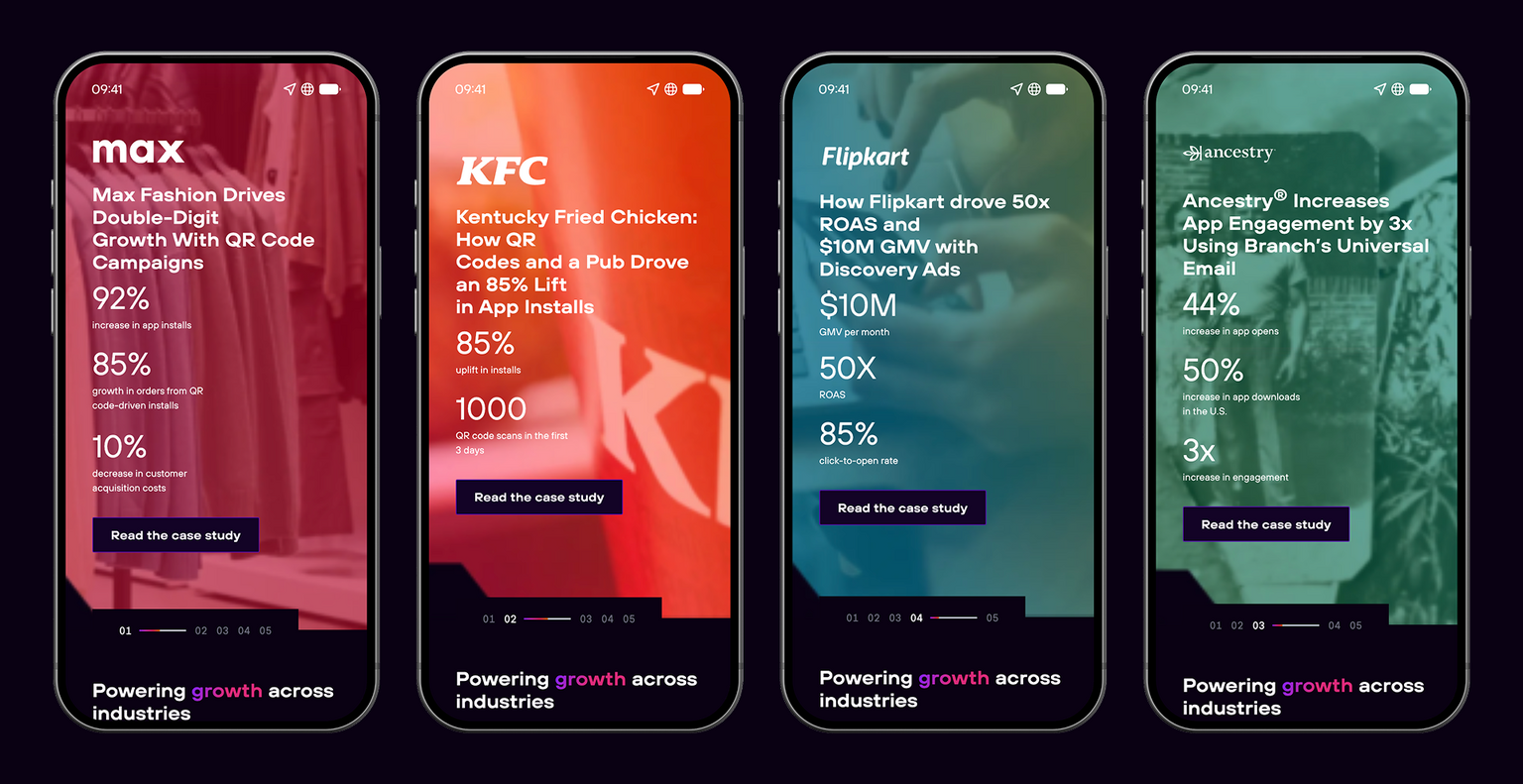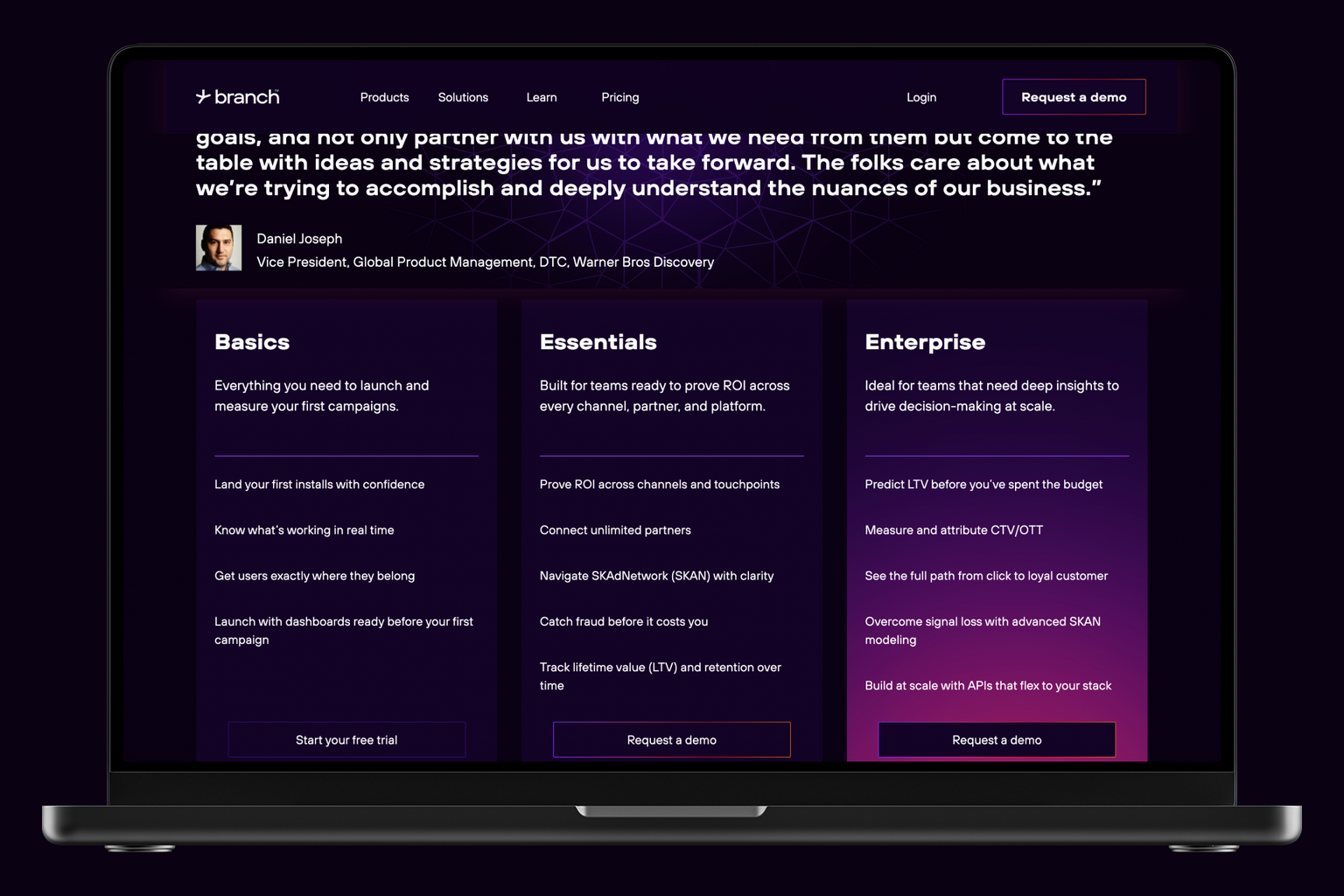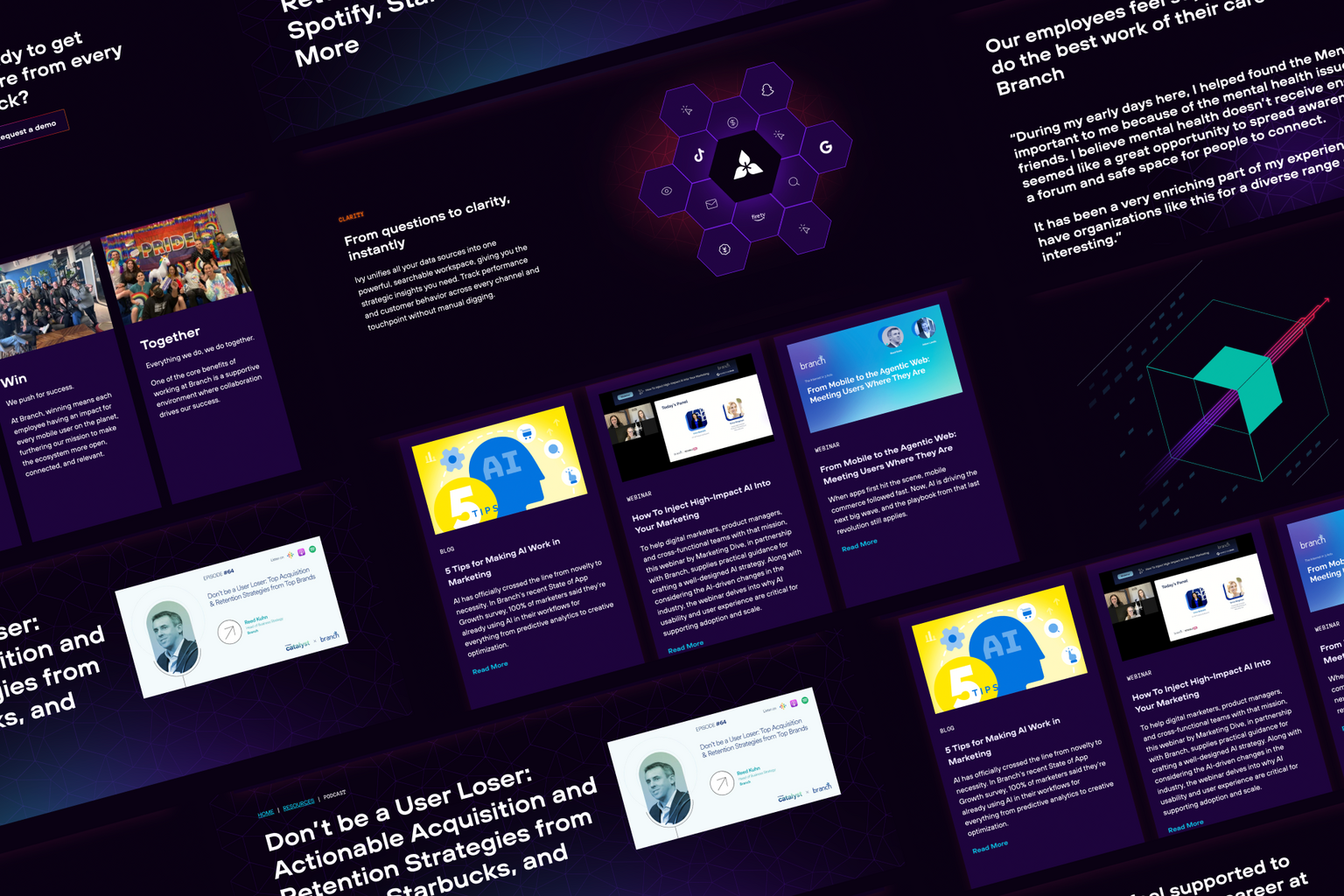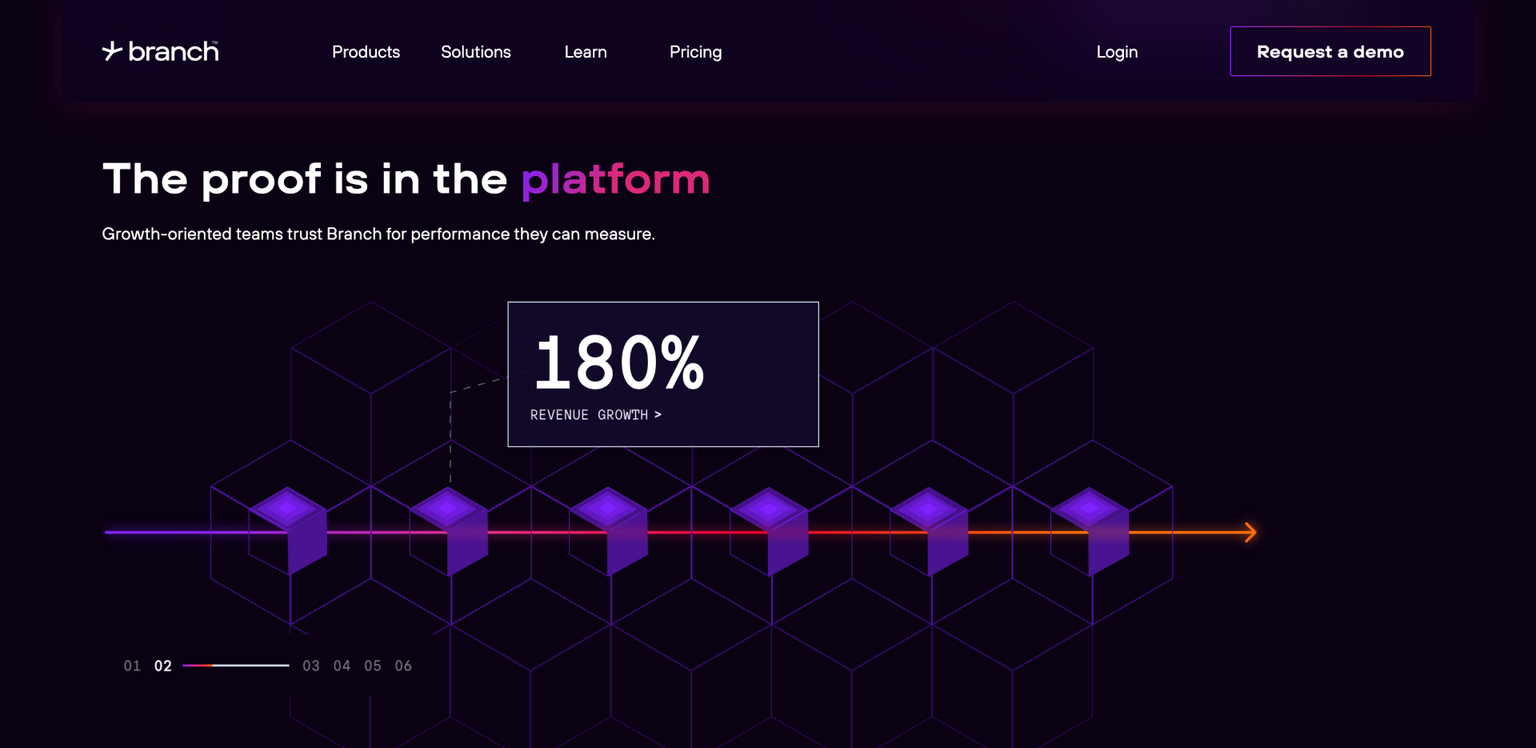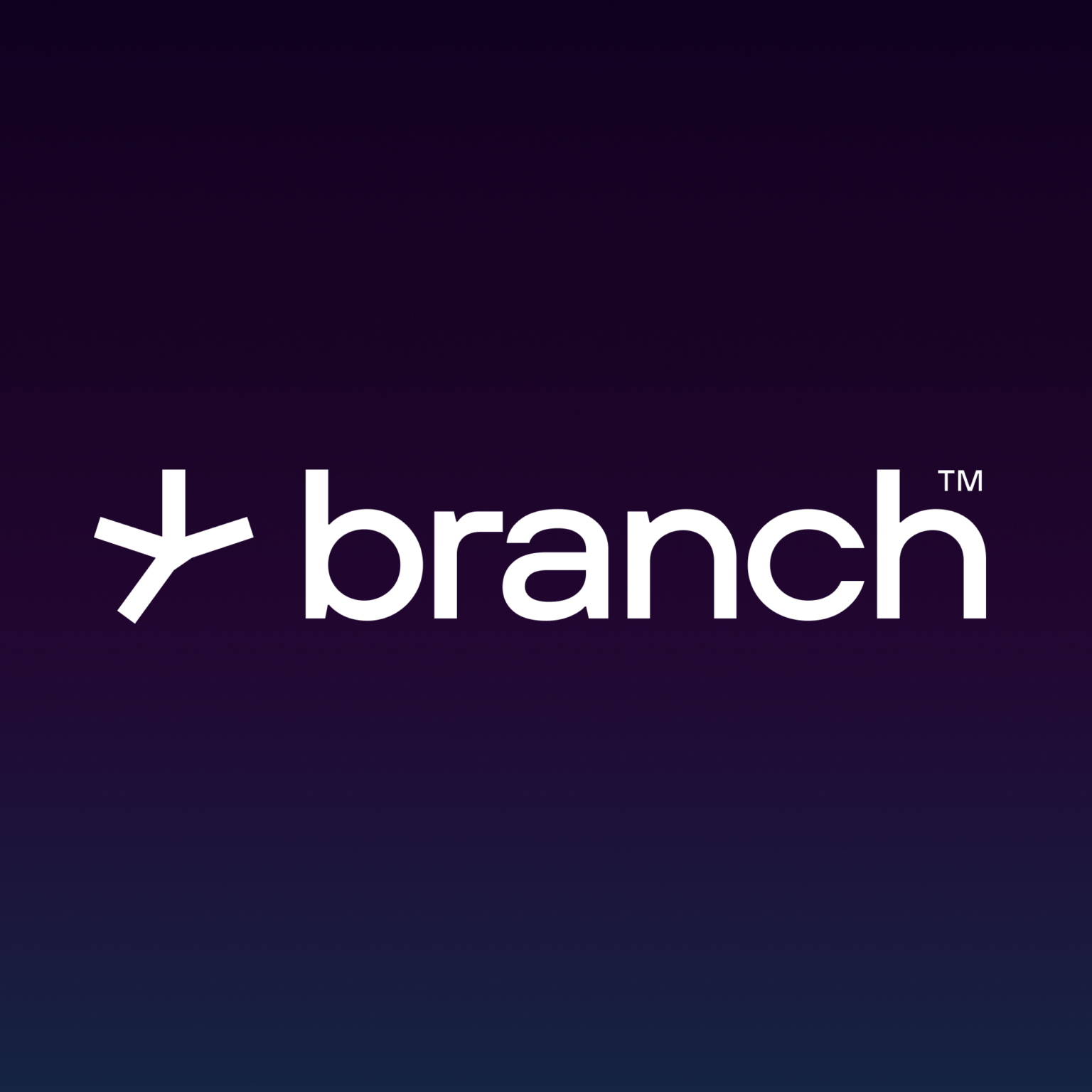
ТТ Ховс Про (TT Hoves Pro) стал фирменным шрифтом компании Branch.io.
Branch — это платформа, которая позволяет рекламодателям и маркетологам отслеживать полный путь пользователя — от первого касания (клик по рекламе, переход из почты, соцсетей и т.д.) до целевого действия (конверсии) в приложении или на сайте. ТТ Ховс Про подчеркнул современный и инновационный тон компании.